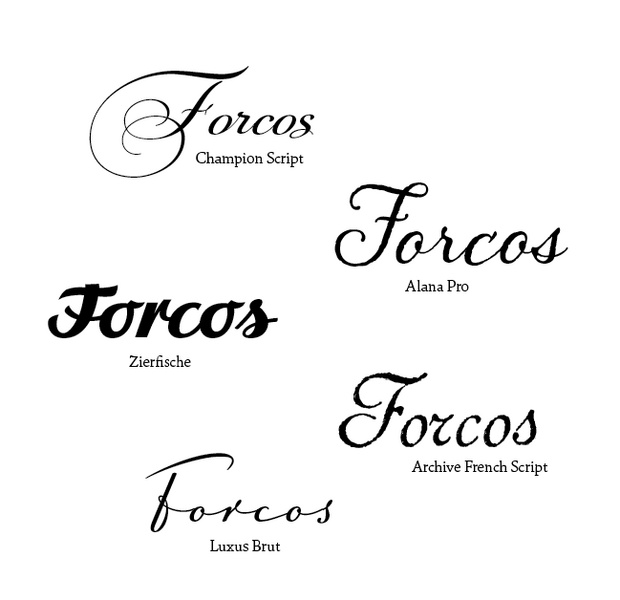
nostalgische Schrift gesucht
wer kennt diese nostalgische Schrift und kennt Alternativen dazu?
Brauche die Schrift für ein Logo.
Ein Plagiat gibt es hier.
Musste leider gerade feststellen, dass mein Firmenname (Forcos) in der Schriftart gar nicht toll aussieht. Die Buchstaben wirken irgenwie nicht harmonisch und nicht so schön flüssig wie bei dem Namen 'Waschmanns' ;-(
Oh je, hat einer ne Alternative? Die Schrift soll auf jeden Fall nostalgisch wirken.
Auch sehr »nostalgisch«:
Movie Script
Oder auch »Retro«?
Folgende Vorschläge hätten den Vorteil, dass sie mit tollen Opentype Features ausgestattet sind. So erhältst Du sehr reizvolle Buchstaben-Verbindungen und -Varianten. Dies wiederum würde Deiner neuen Marke neben der entstehenden Dynamik auch mehr Einzigartigkeit verleihen.
Vorschläge der argentinischen Schriftenschmiede Sudtipos:
· Candy Script
· Calgary Script
· Suggar Pie
Vorschläge von Underware:
· Bello
· Liza
Auch sehr »nostalgisch«:
Movie Script
An und für sich eine schöne Schrift, aber mit den Outlines ist sie absolut unbrauchbar.
Ist diese Autotrace-Optik Absicht, oder wurden da alte Schriftmuster mal eben durch Illustrator gejagt?
Stelle gerade fest, je mehr man sich mit Schriften befasst und sich anschaut, je schwerer ist die Entscheidung für eine davon.
@Robert: Ja, auch Retro. Trifft es vllt. sogar noch besser ;-)
Die Movie Script ist mir für den Firmenname leider zu "unleserlich" und vom Stil her zu hart.
Im Logo ist ein alter Doppeldecker. Schrift sollte daher zu den 30er, 40er Jahren passen.
Die Movie Script ist mir für den Firmenname leider zu "unleserlich" und vom Stil her zu hart.
Da stimme ich Dir gerne zu. War eher ein spontaner Einfall, weil wir letztens ein ähnliches Thema hier hatten. Außerdem ist ja »nostalgisch« ein sehr dehnbarer Begriff. Damit wollte ich einfach auch testen, wie wichtig Dir es damit ist, und was Du darunter verstehst.
Schrift sollte daher zu den 30er, 40er Jahren passen.
Diese Eingrenzung hilft da schon enorm weiter. Auch der Doppeldecker-Hinweis ist wichtig. Denn jetzt würden für mich schon mal alle Schwergewichte wie die Bello ausscheiden. Hier wird also deutlich: um so klarer Du selbst den »Markenkern« beschreiben kannst, umso leichter wird es fallen, den richtigen und treffenden Font aus dem großen Angebot auszuwählen. Denn am Ende soll Dein Erscheinungsbild ja vor allem authentisch sein.
Das spuckt die Myfonts-Suche jetzt aus: Coffee Service oder Filmotype LaSalle
Da könnte man also auch noch die Calgary Script gelten lassen. ;-)
Statt script kannst du natürlich auch brush oder was auch immer eingeben.
Schrift in Pfade umwandeln und für Logos verändern ist eigentlich eine gängige Sache. Gerade bei Scriptschriften gibt es da manchmal Optimierungsbedarf.
Dennoch lohnt sich meistens ein Blick in die EULA, denn anscheinend gelten für die Benutzung der Schrift in Logos manchmal andere Bestimmungen.
Mir gefiele auch die Gabrielle (2. Schrift) von Dieter Steffmann ganz gut, die erste ebenfalls von Steffmann die Forelle weniger ist aber auch Retro (ich hatte sie schon stehen und wollte sie nicht noch löschen).
Die unteren beiden Schriftzüge sind aus der Buffalo Nickel von Nick Curtis gesetzt, welche der Script MT sehr ähnlich sieht, aber etwas anders läuft. Unten habe ich einen Fehler beim F entfernt und das S am Ende auf die schnelle abgerundet.
All diese Schriften sind kostenlos.
Die Magesta Script finde ich vom "Schwung" her bzw. insgesamt sehr schön. Habe nur meine Bedenken wegen dem "Stempelartigen" ob das z. B. auch beim Druck, Faxen o. ä. gut rüber kommt!?
@Vitrioloel: Vielen Dank für den Tipp und die Mühe mit dem Abändern. Schriften sehr schön, aber die Buffalo Nickel trifft es gut.
... aber die Buffalo Nickel trifft es gut.
Hier würde ich für ein (deutsches) Logo das ›F‹ ändern, das sieht m. E. noch zu sehr nach ›J‹ aus. Nicht, dass unbedingt Verwechslungsgefahr besteht, aber etwas eindeutiger fänd’ ich es besser.